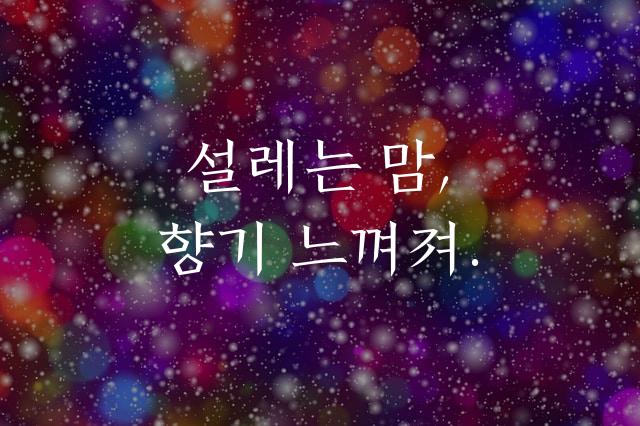
전주완판본 순체는 전주시청에서 제작한 클래식한 바탕체 폰트로, 각진 디자인이 돋보이며 한글의 전통적 아름다움을 현대적 감각으로 재해석한 작품입니다. 이 폰트는 세련된 분위기와 함께 역사적 울림을 제공합니다.
전주완판본 순체은(는)
바탕 스타일, 명조/전통, 네모꼴, 복고풍, 단단함 계열의 생김새를 가지고 있으며
출판 디자인, 초대장, 출판물 제목 등에서 자주 활용되며, 효과적인 메시지 전달에 적합합니다.
이 폰트는 출판/미디어, 문화/예술, 이벤트/웨딩 분야에 잘 어울리며,
전통적, 편안한, 클래식한 느낌을 담고 있는 것이 특징입니다.